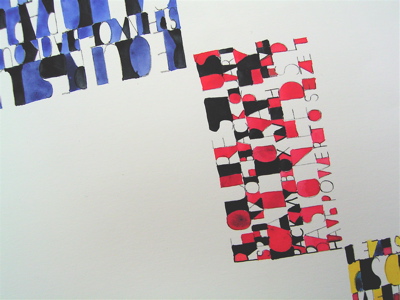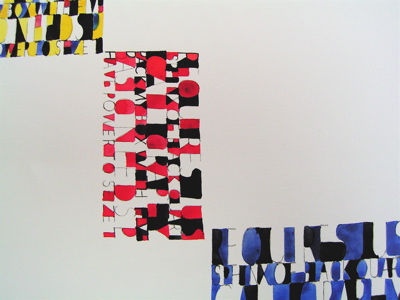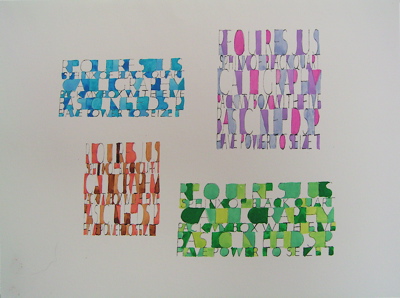
スケルトンの練習
クラスでローマンキャピタルをやるときは、鉛筆のスケルトンから入ります。
ペンではなく、まず鉛筆でじっくりと進めます。なんといってもスケルトンを理解しないと、ペンになってもうまく形を取れないからね。特にスペーシングはじっくり取り組みます。
たった26文字ですが、大体4回くらいかけてやるのです。というのも、スケルトンでスペーシングも一緒にやっていくと、それくらいになってしまいます。
退屈やわ〜、と思うかもしれませんが、なんとかそこを我慢して頂き、高さが2.5センチくらいの大きなスケルトンで文章を書けるまできちんとやりたいのです。
何度も言うけど、だってローマンは大事だからね。
で、鉛筆ばかりではツマンナイになってしまいがちなので、こんな風に水彩色鉛筆で書いて、レタースペースを水で溶かして色塗りです。
生徒さんのmayumiさんは、こんなにたくさん書いて来られました。
おもしろいテクスチャーですね。
こうして文字のカウンタースペースを塗ったり、レタースペースの形を残したりしていると、だんだん文字の構造や形やその文字が持っているスペースや、その他いろいろ見えて来るのです。
mayumiさんは、もっと宿題をやってきました。
黒を入れただけで、とてもモダンになって幾何学模様がはっきり見えて来ますね。
ご本人は、変になったと恐縮しておられましたが、いえいえとっても面白くていいですよ!
よ〜く考えよ〜、
ローマンキャピタルは(ここんとこ早口で)大事だよ〜、
きれいな形と完璧なスペーシングのスケルトンなら、十分に作品にもなります。
いつかじっくりローマンのスケルトンに取り組んで、おもしろい作品作ってみたいなぁ〜。
他の書体に行っても何度も戻りつつ、自分のものにして行くのがローマンキャピタルですよね、復習復習!
今まさにローマンを練習中です。
こんな正確に書くなんて無理くね?と思っていましたが
実際書いてみるとすごく楽しいです。
なかなか理想の形、スペーシングには遠いですが
頑張って練習しなくては。